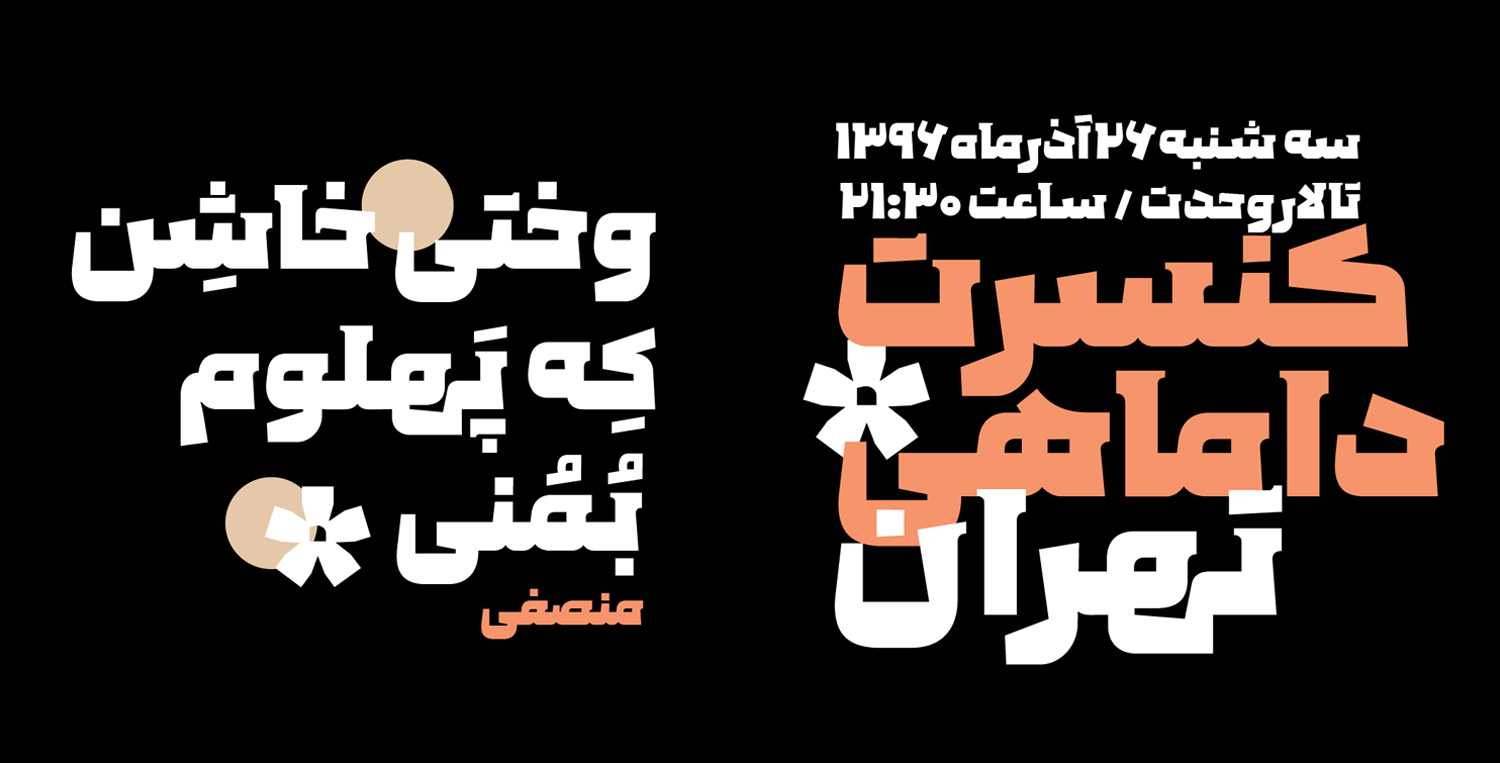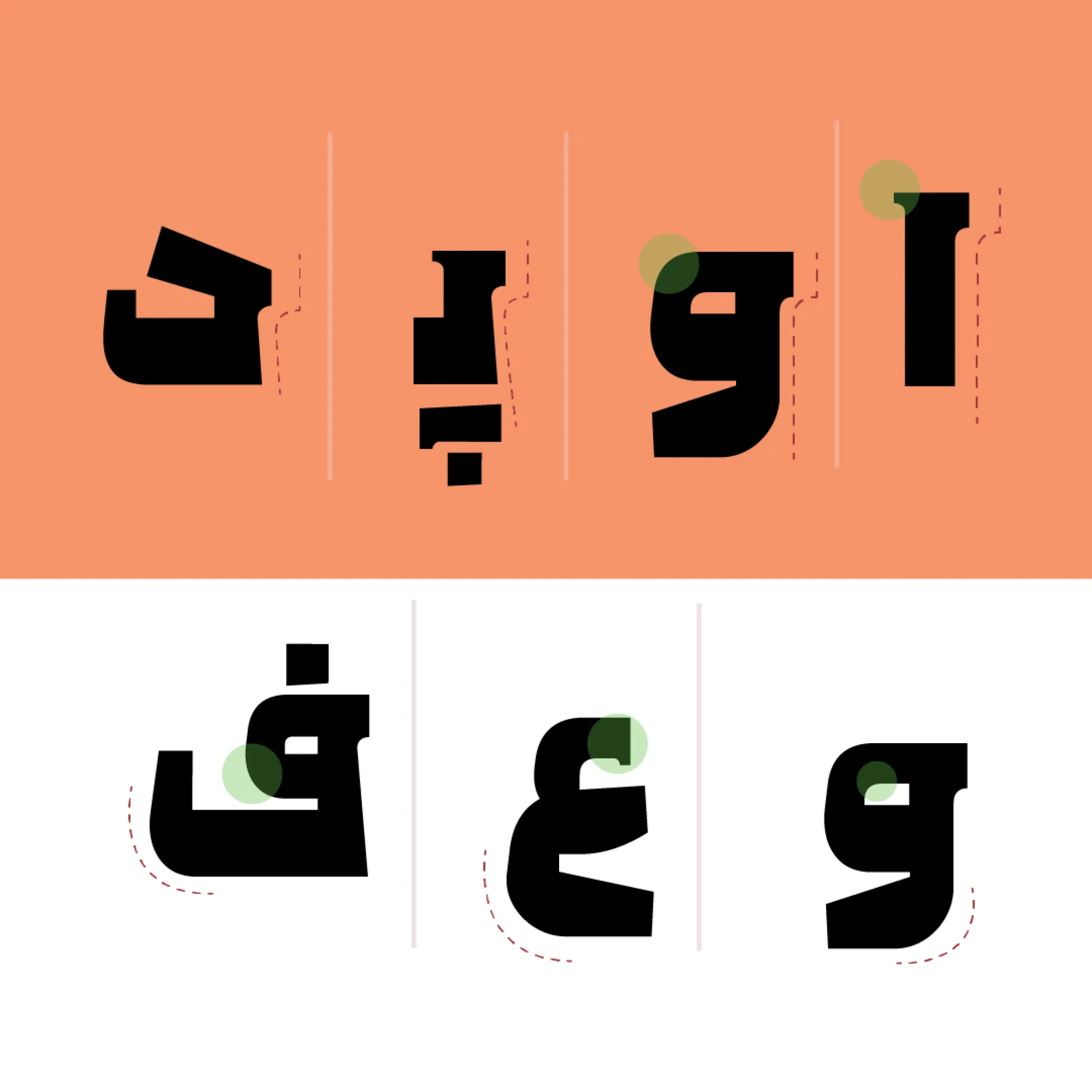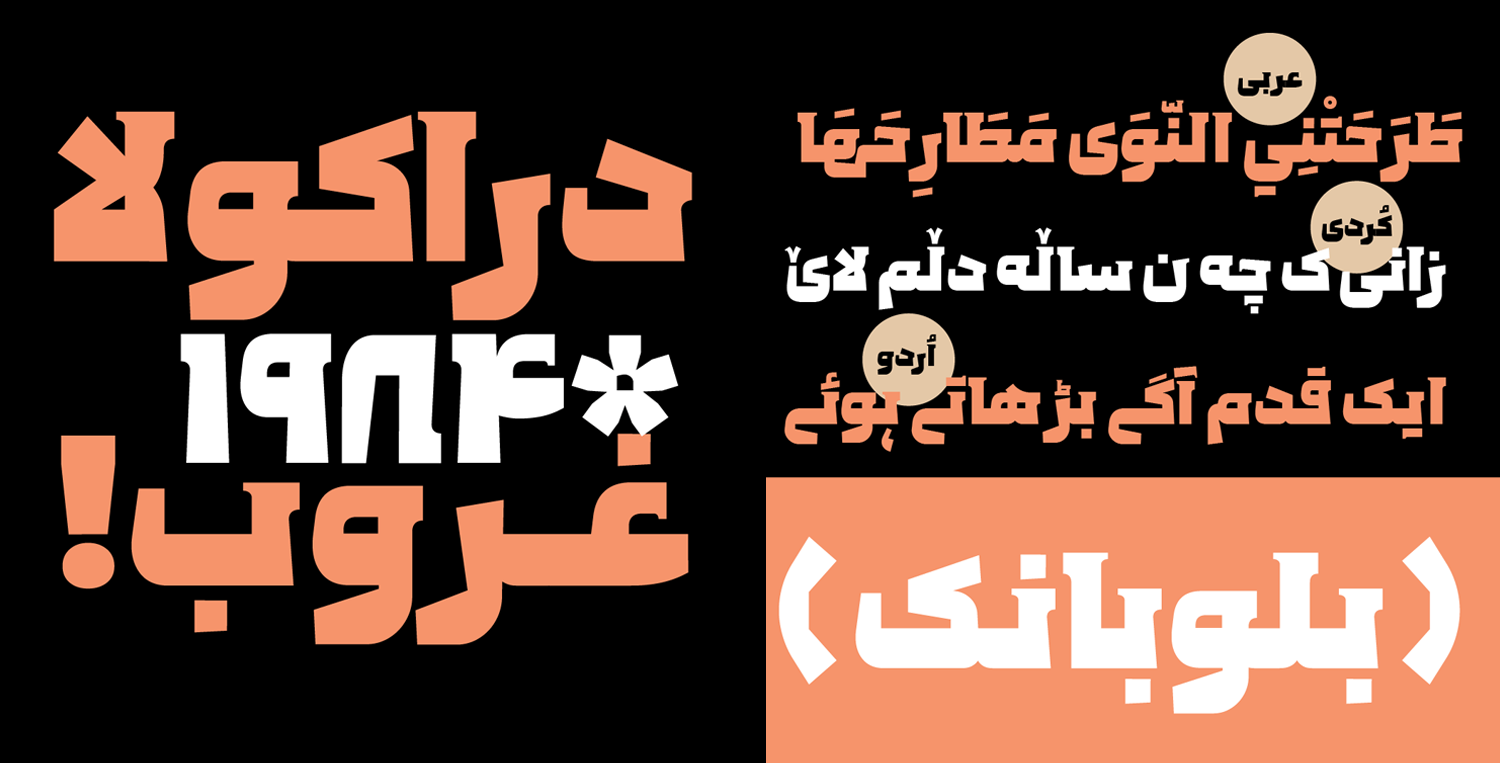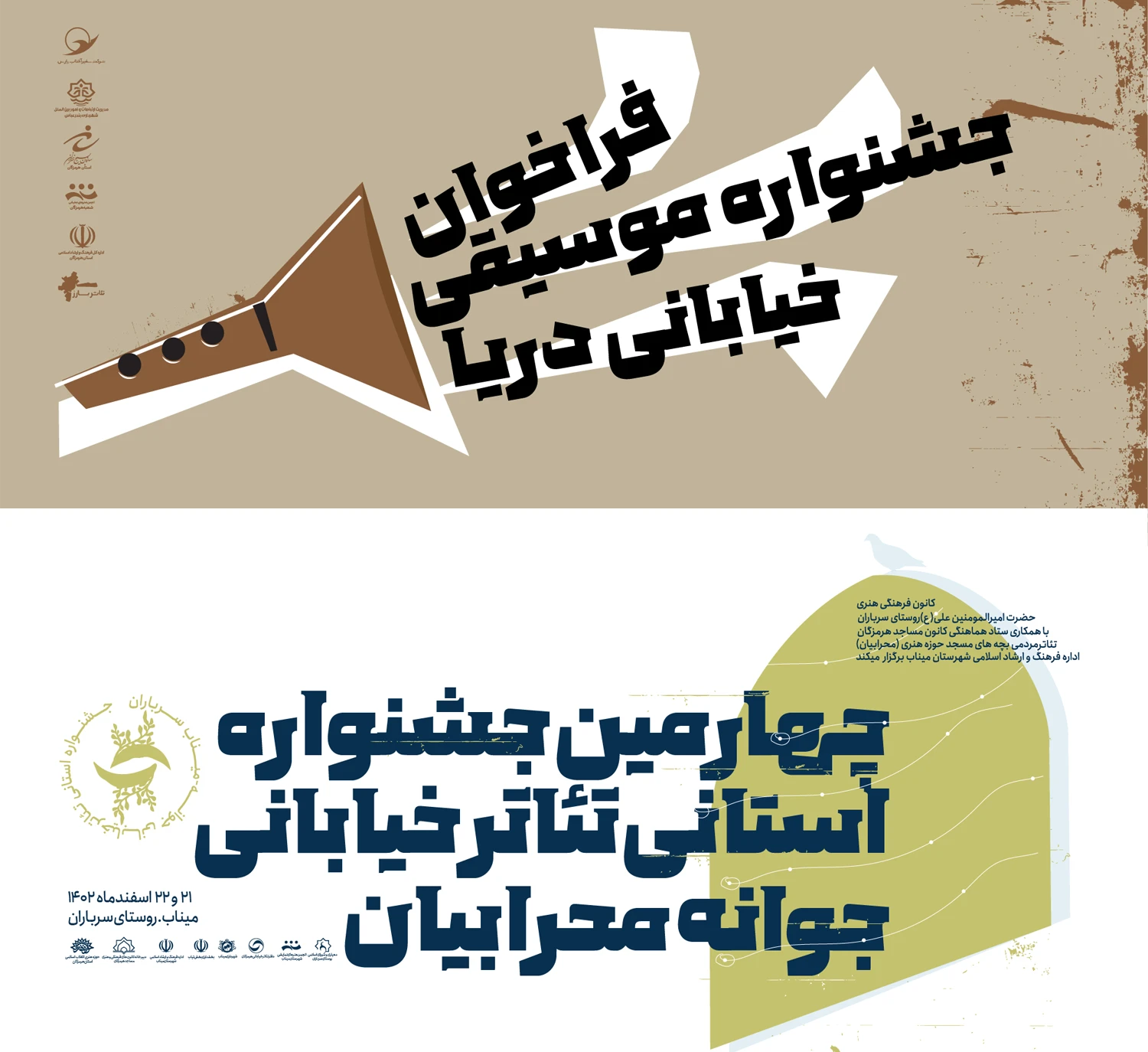
فونت پولاد (Pulad)
فونت پولاد (به انگلیسی: Pulad) قلمی با سبک هندسی است که دارای ساختاری کاملا نمایشی و شخصیتی جسور است که میتوانید از این قلم برای کارهای مختلفی همچون عناوین، تبلیغات و متون کوتاه از آن استفاده کنید. ظهر این فونت بهگونهای است که پیش از این چنین طراحی را در فونت والهالا دیدهایم.
یونس دهقانی، طراح گرفیک و دیزاینر فونت این قلم را با هدف استفاده برای متون کوتاه بهویژه در عناوین کتب و مجلات طرحی کرده است که در ادامه به نقد و بررسی کامل این فونت میپردازیم.
فونت پولاد قلمی با وزن Black است که ساختار طراحی آن بهگونهای است که دارای ظاهری سیاه بهنظر میرسد. این فونت شخصیتی جسور دارد، از یک سبک نقطه گذاری خاص بهره میبرد و از همه مهمتر ظاهر و چینش حروف بهگونهای است که ساختاری مستحکم به کلمات میدهد.
با وجود ینکه این قلم ظاهری جدی دارد، اما در عینحال هندسهی دلنشین در دل خود جای داده است. میتوانید از این قلم در فضاهای تبلیغاتی، به ویژه در شبکههای اجتماعی استفاده کنید که ظاهری مستحکم و جسور به محتوای شما خواهد داد.
در ادامه تصاویری از این قلم را در محیطهای مختلف مشاهده میکنید که میتواند برای استفاده در موبایل و دسکتاپ نیز مورد استفاده قرار گیرد. در فضای غیر دیجیتال نیز میتوان از این قلم در تبلیغات محیطی، بهویژه بیلبوردها استفاده کرد.
فونت پولاد از زبانهای فارسی، عربی، انگلیسی، کوردی و اردو پشتیبانی کاملی دارد که شامل تمامی حروف، اعداد و کاراکترهای خاص هر زبان است.